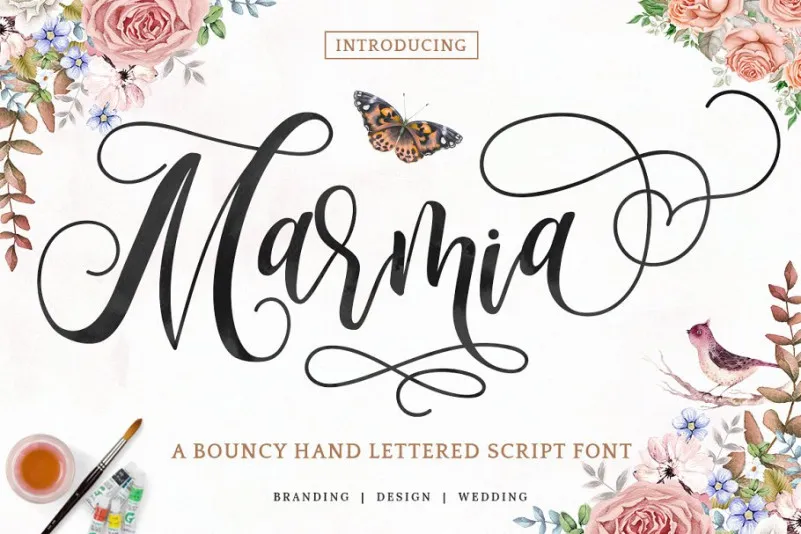
Marmia Calligraphy Font
Amantes do tipo! Aqui está uma nova fonte chamada Marmia para vocês explorarem. Lançamos essa elegante fonte de calligrafia com o objetivo de tornar suas criações mais sofisticadas e criativas. Cria por Kotak Kuning Studio, Marmia foi desenvolvida para quem busca um elemento de charme natural em seus designs digitais. Quer seja para criar mensagens de estilo elegante ou simplesmente dar uma pitada de classe a seus trabalhos gráficos, essa fonte tem ligaturas e alternativas de caracteres naturais que permitem que ela se assemelhe cada vez mais à escrita manual. Através de sua abordagem OpenType, Marmia oferece um sentido vivo e verdadeiro do estilo de escrever, tornando-a uma opção perfeita para aqueles que buscam algo autêntico em seu trabalho visual. Estamos ansiosos para vê-los experimentarem Marmia, se apaixonarem por sua elegância e criatividade natural. Que tal você adicionar a sua próxima design ao seu portfolio?